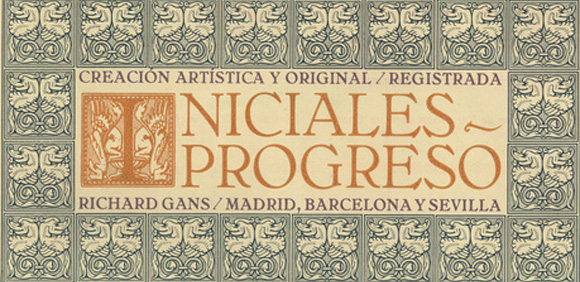
Dentro de la tradición de unostiposduros para revitalizar la tipografía española así como la recuperación de aquellos alfabetos de la otrora floreciente industria tipográfica del siglo XIX y XX, os presentamos un nuevo set de Flickr del especimen que editó la fundición tipográfica Richard Gans de Madrid para el conjunto de «Inicales Progreso», conjunto de capitulares floreadas u ornadas en cuerpos 44, 66 y 88 puntos didot, que se servían sólo para inicios de párrafo tanto en plomo como en galvano —plumas—. Si tenéis algún especimen y lo queréis vender, no dudéis en contacta conmigo, bien en lletraorama(arroba)gmail.com o en el 655 77 15 30 —exclusivamente en horario de mañana—. También si queréis subirlos a un sitio público y queréis que demos cuenta de ello.